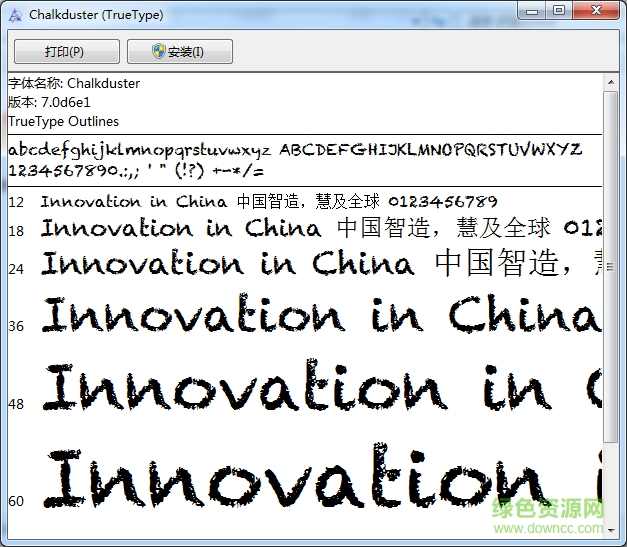
chalkduster中文字體
chalkduster是一款手寫效果的中文粉筆字體,如同粉筆在黑板上書寫的模式,給人一股濃烈的校園生活的獨(dú)特體驗(yàn),適合校園主題和懷念系列的作品使用,綠色資源網(wǎng)你誠意推薦!
chalkduster字體特色
chalkduster中文版就像是用一根粉筆寫在黑板上那樣,有著醒目的視覺和學(xué)生時(shí)代的記憶重現(xiàn)的美感,可使用在校園生活的宣傳和內(nèi)容上,當(dāng)然,在平面設(shè)計(jì)、海報(bào)設(shè)計(jì)、排版印刷中也可以使用!